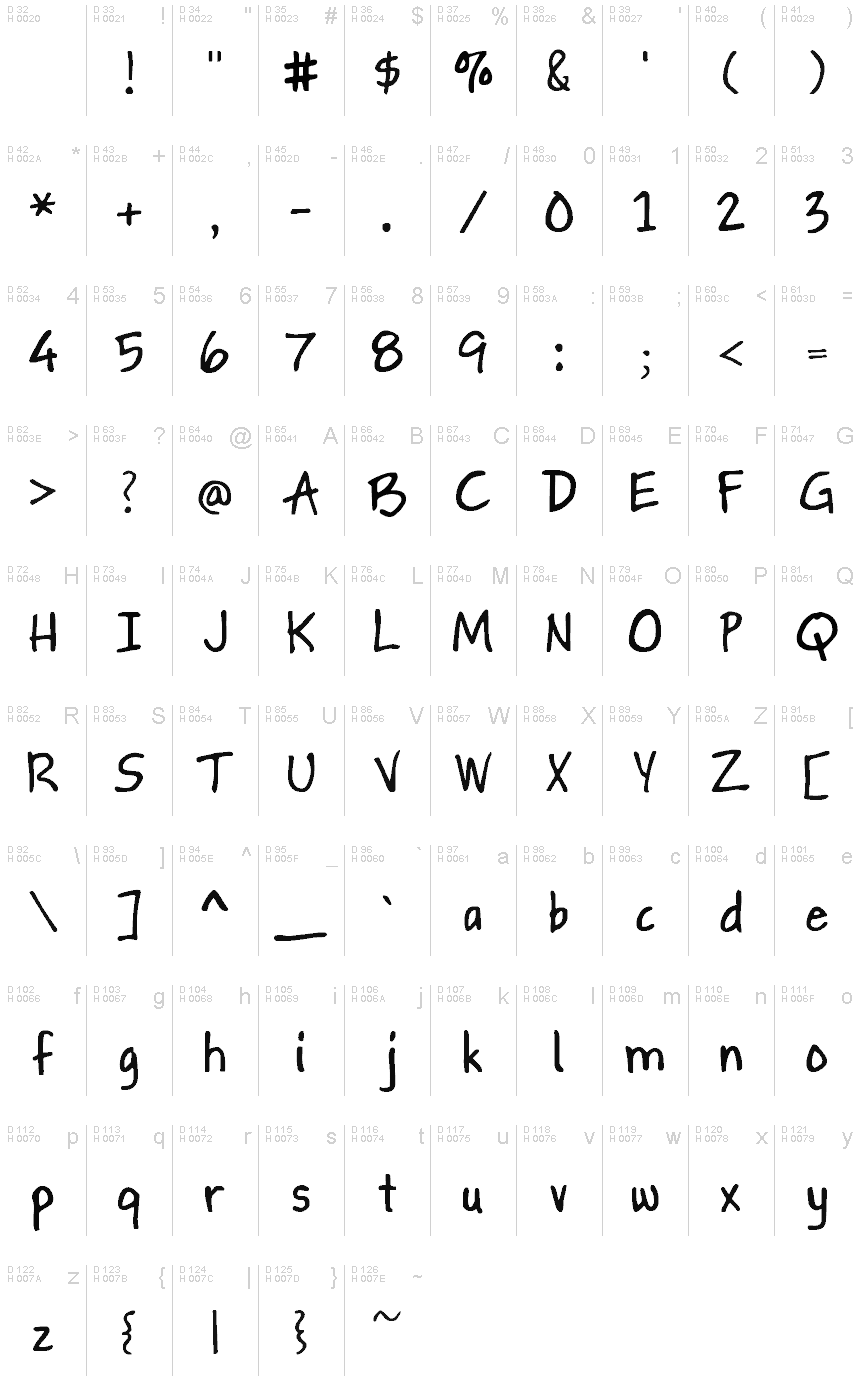
Gapstown AH von Fontgrube ist eine kostenlose, handgeschriebene Schrift, die den Look einer schnellen, souveränen Marker-Notiz einfängt – ganz ohne Klecksen. Dank der abgerundeten Striche, großzügigen Kurven und eines leicht unebenen Rhythmus wirkt das Schriftbild sympathisch und menschlich, bleibt dabei aber auch in kleineren Größen stets sauber und gut lesbar. Sie vermittelt eine lockere, informelle Energie, wie bei einer Notiz auf einem Whiteboard oder einem Post-it, und verleiht Ihrer Botschaft eine nahbare statt steife Note.
Mit Gapstown AH verleihen Sie Arbeitsblättern, Kinderprojekten, lässigen Postern, Instagram-Grafiken, Produktetiketten, Grußkarten und handgeschriebenen Zitaten eine warme, persönliche Note. Die luftige Laufweite verhindert, dass der Text gequetscht wirkt, und die gleichmäßige Strichstärke überzeugt sowohl am Bildschirm als auch im Druck. Diese kostenlose Schrift harmoniert wunderbar mit einer einfachen geometrischen serifenlosen Schrift für den Fließtext – setzen Sie Gapstown AH für Überschriften und kurze Phrasen ein und überlassen Sie der Sans den längeren Text.
A handwriting font with informal but not too irregular characters, for those who are kind of tired of the standard
hand printing fonts supplied by Creative Suites and commercial operating systems, the ones you see everywhere. These
are fairly unknown faces and a good alternative.
Gapstown comes in two weights, standard and bold, and in two variants: Gapstown and Gapstown Small. The latter has
wider letterspacing for smaller print sizes. Test for yourself which ones to use at what size.